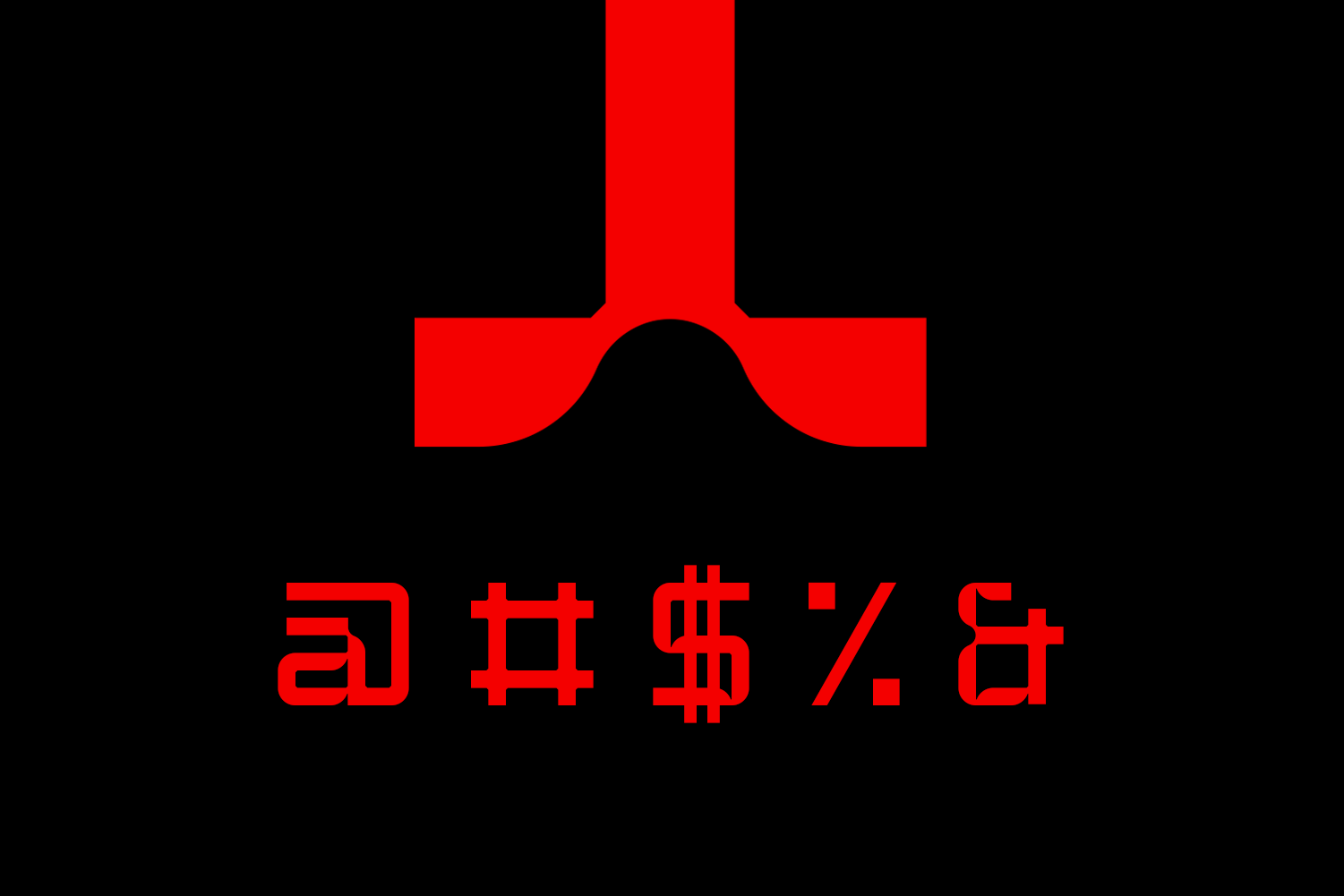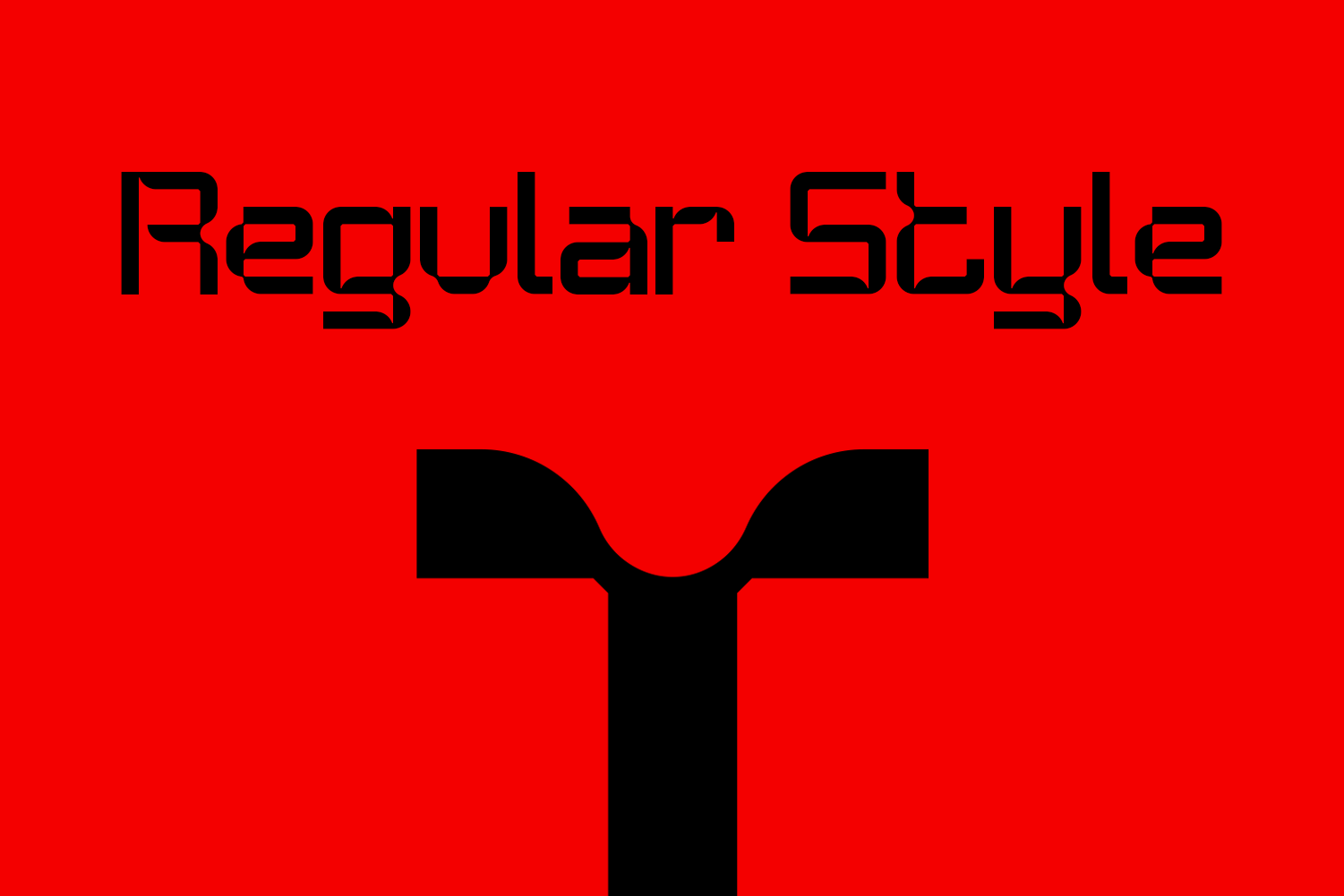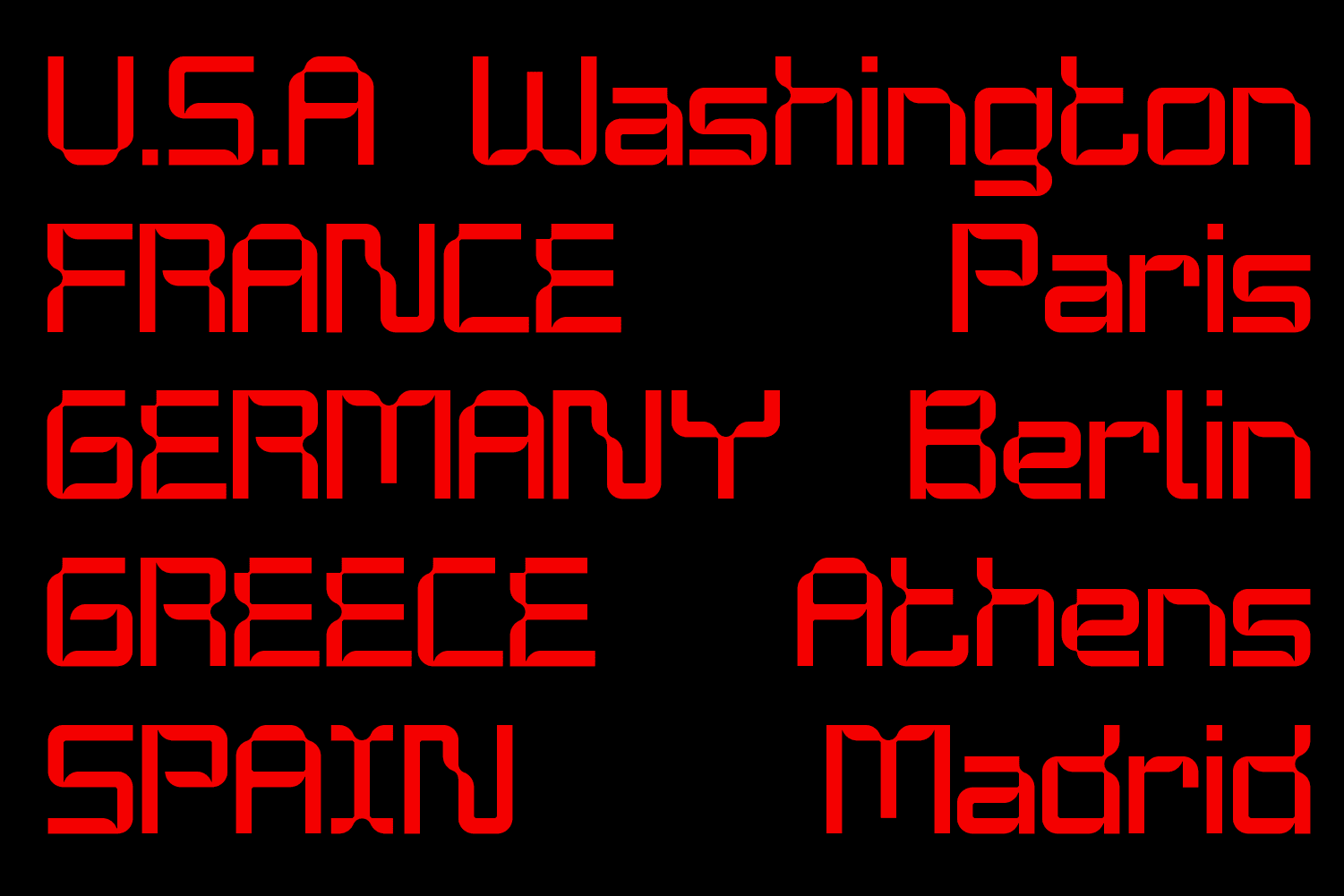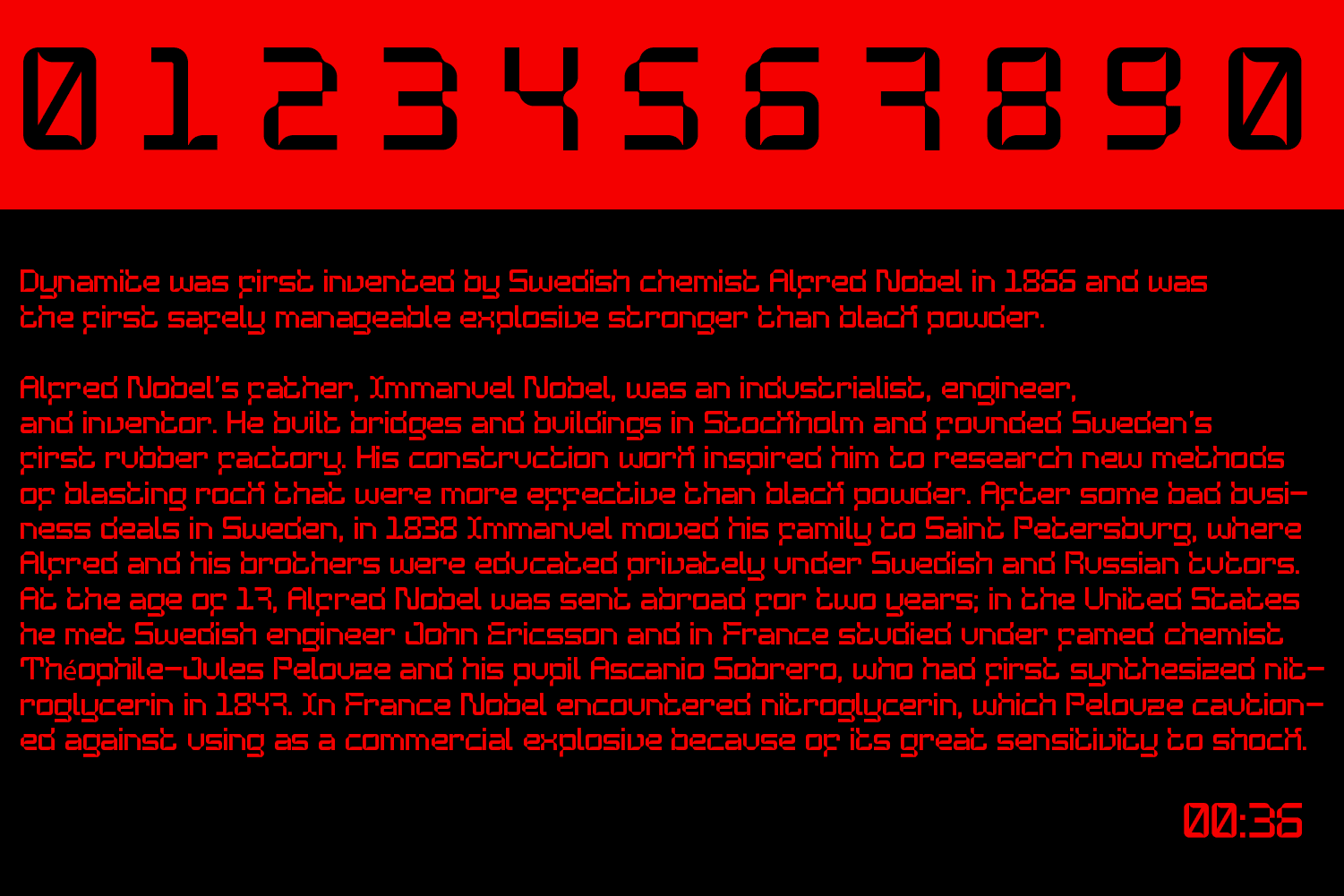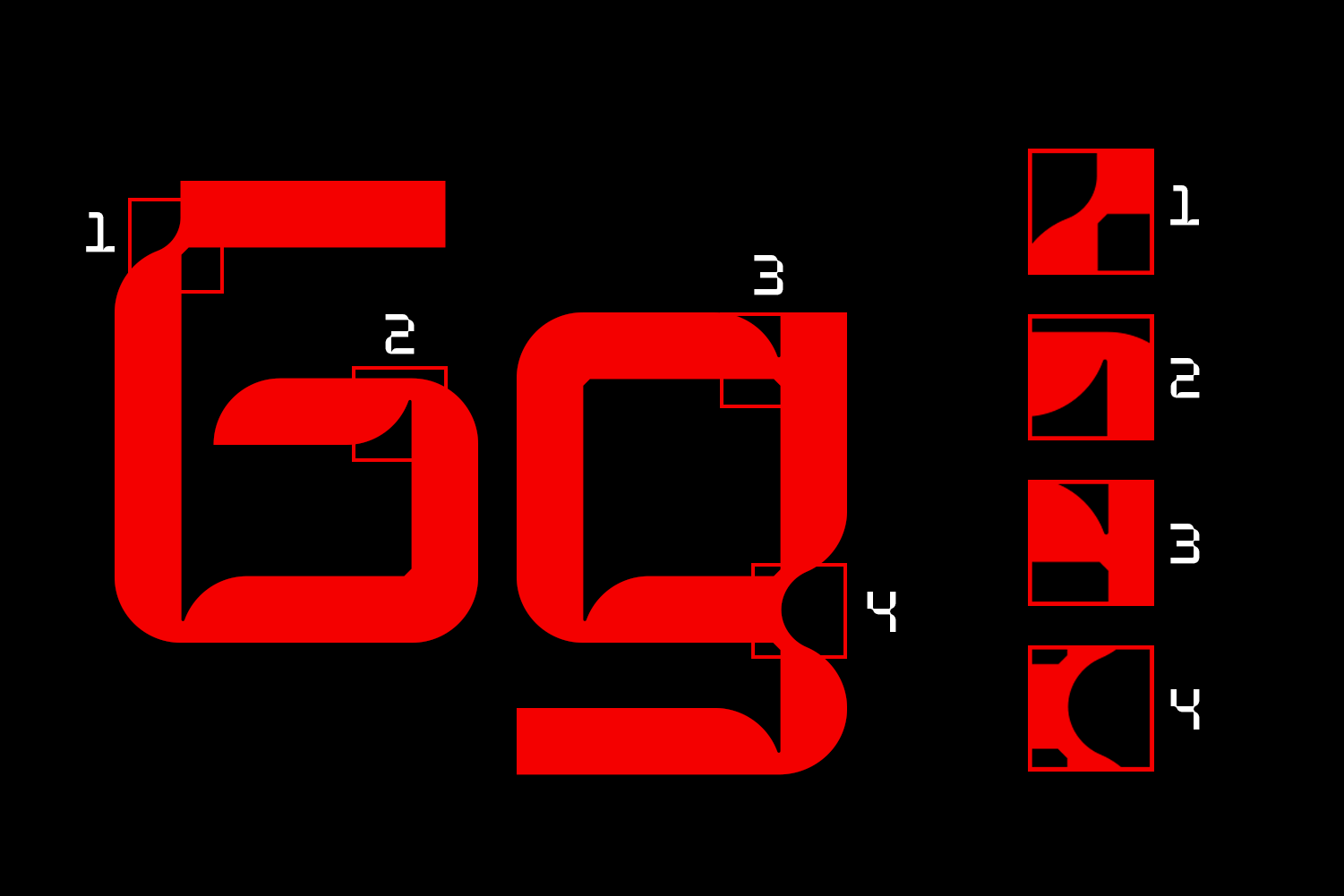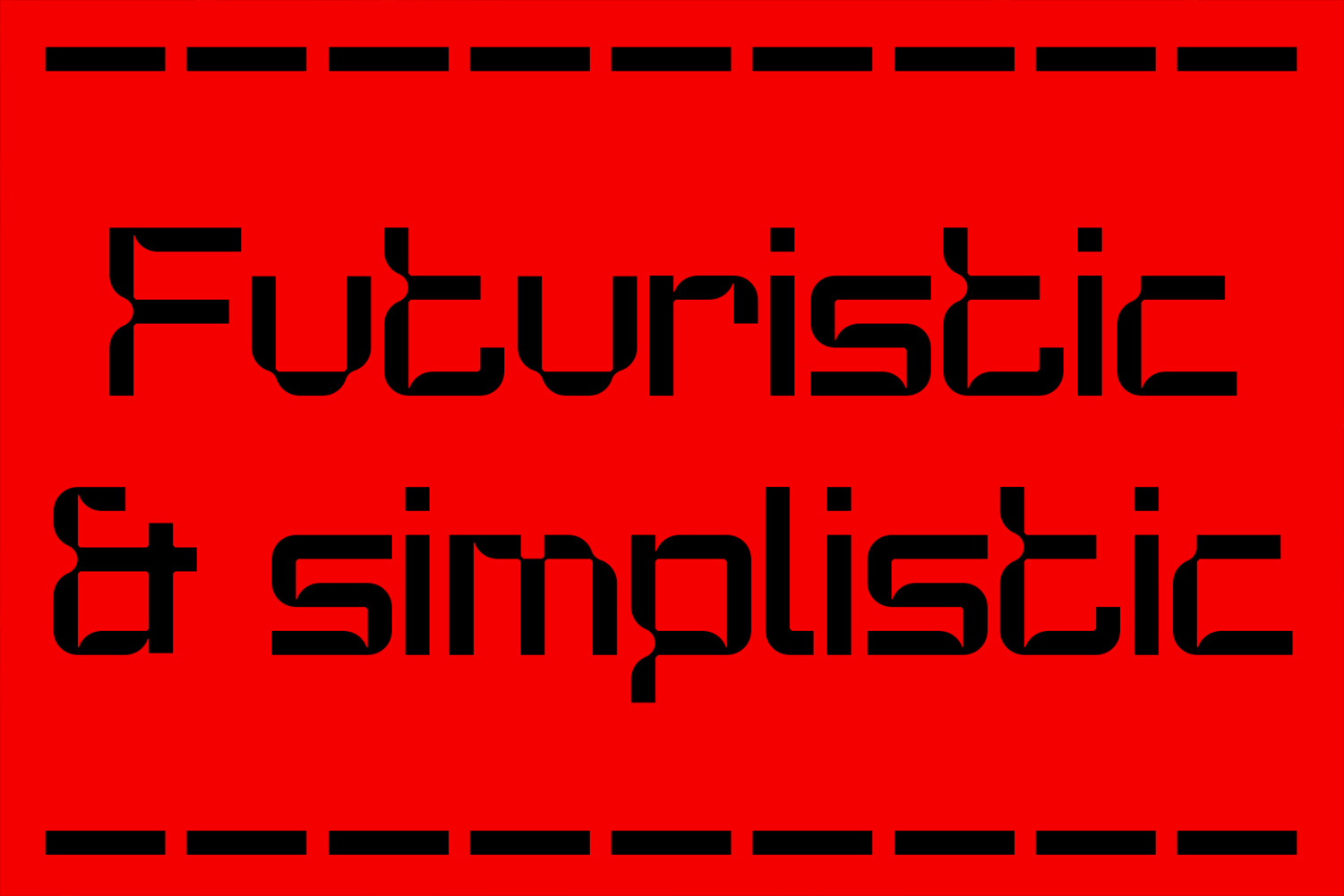
MANG LẠI PHONG CÁCH TƯƠNG LAI, HIỆN ĐẠI ĐƯỢC LẤY CẢM HỨNG BỞI PHONG CÁCH ĐƠN GIẢN, Bùng nổ, MẶT BẰNG KIỂU NÀY HOÀN HẢO ĐỂ THỂ HIỆN PHẦN TƯỞNG TƯỞNG CỦA BẠN.